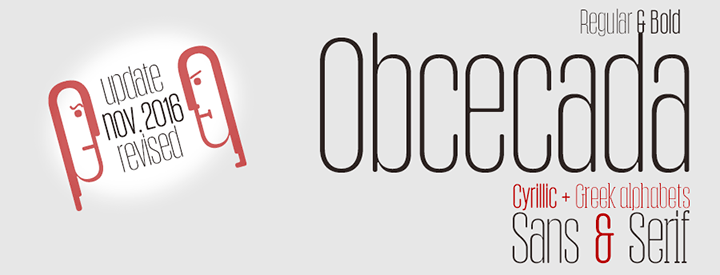
Obcecada Sans & Serif son dos tipografías digitales geométricas en [...]
Obcecada Sans & Serif Condensed
Obcecada Sans & Serif son dos tipografías digitales geométricas en versiones regular y negrita, muy condensadas y finas con acabado redondeado en las astas y uniones con un estilo moderno. Incluyen el alfabeto cirílico y griego. Estas fuentes son fruto de mi obstinación por tipografías muy condensadas, en este caso me he inclinado por una […]